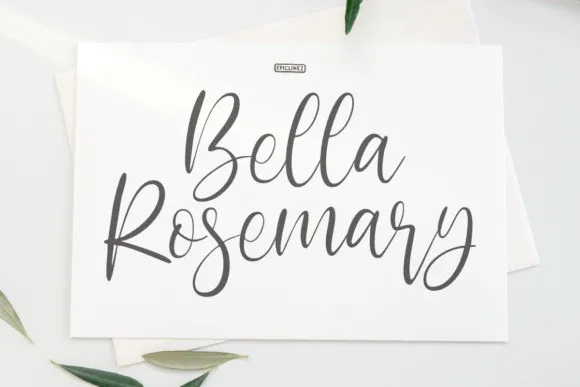
Esta font script com destaque contemporâneo e sofisticado. Foi criada pelo font designer conhecido como Epiclinez. É uma escolha ótima para criar logomarcas, marcas de marca e citações memoráveis. Cada letra traz um toque único e belo, tornando seu design viver em movimento. Adote a Bella Rosemary Font se você está procurando por uma font script que irá trazer vida e originalidade para seus projetos digitais. Perfeita tanto para trabalhos profissionais quanto para criações de arte pessoal, essa font atende à necessidade de um design moderno e sofisticado. Não perca tempo, sua ideia pode ganhar vida agora com a Bella Rosemary Font!